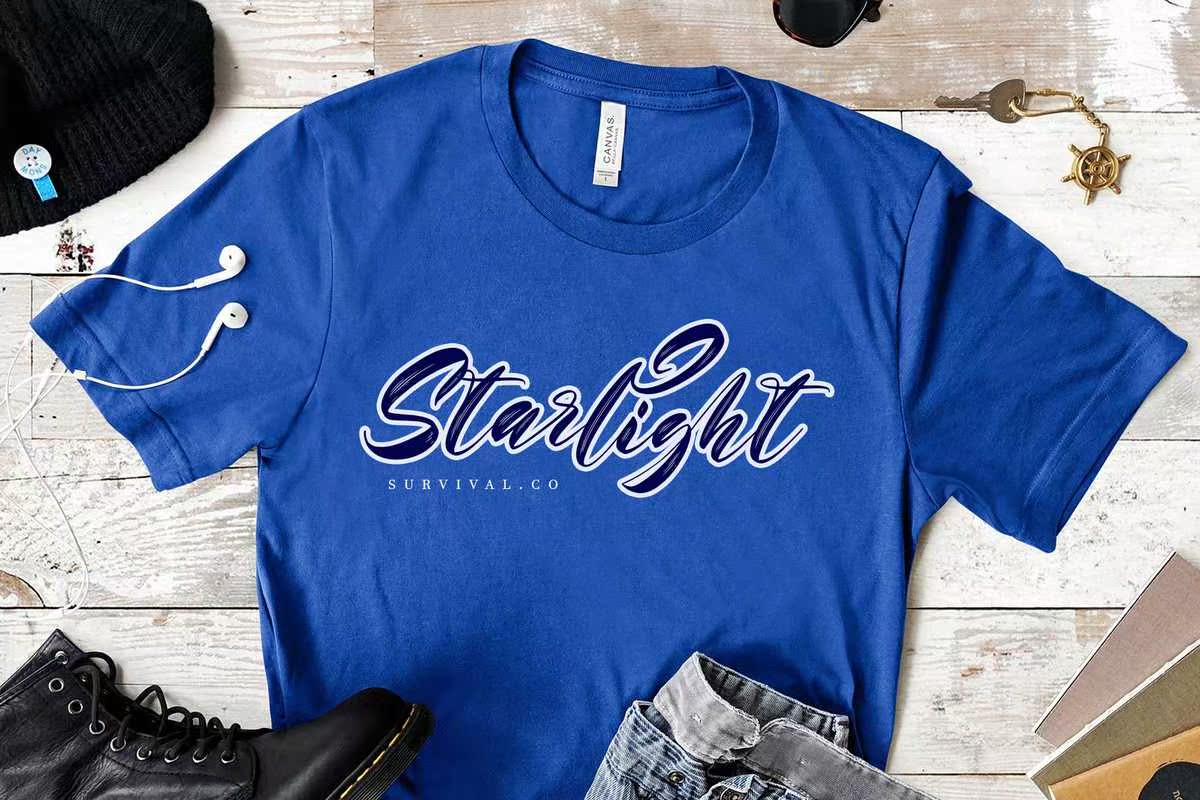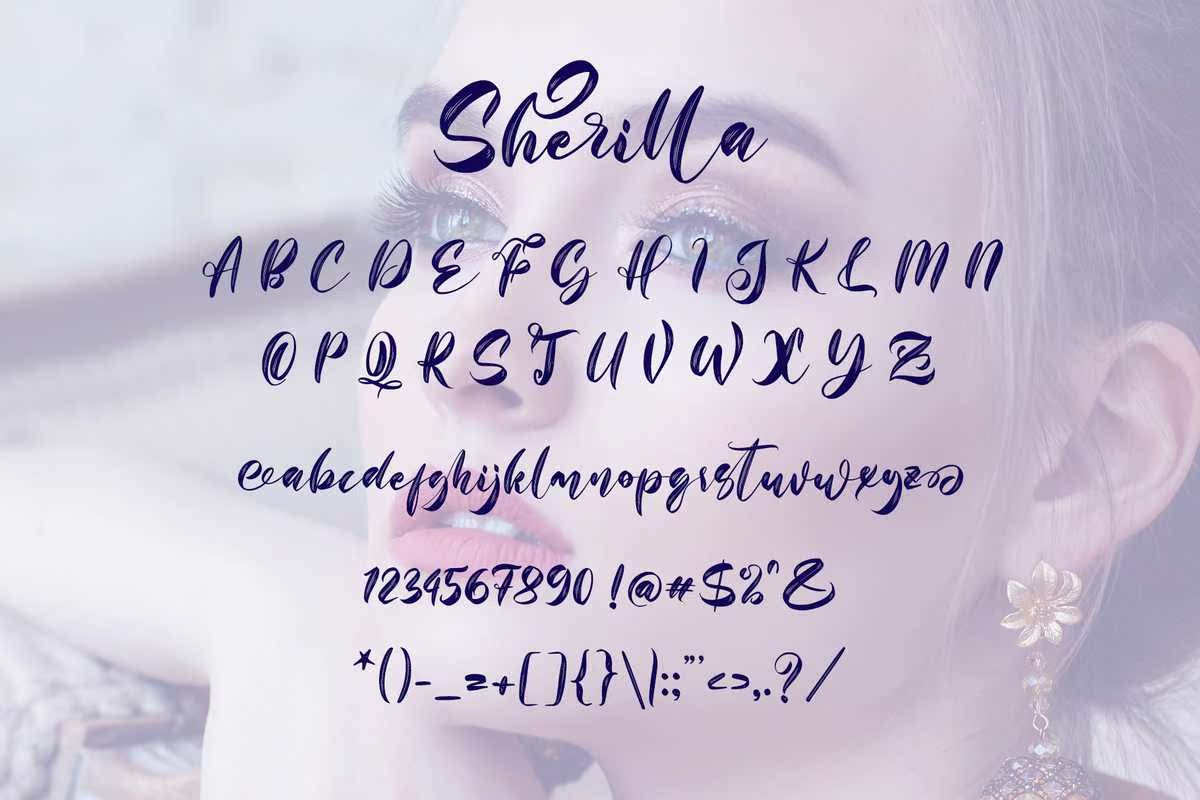
Sheilla是一款精美、精致的系列服装。它是一款优雅、时尚的服装,可用于制作日志、品牌、邀请函、文具、婚礼设计、社交媒体等等!这个字体是经过编码的,意味着你可以访问所有的符号和SWASHEASE!Sheilla是一款精美、精致的系列服装。它是一款优雅、时尚的服装,可用于制作日志、品牌、邀请函、文具、婚礼设计、社交媒体等等!这个字体是经过编码的,意味着你可以访问所有的符号和SWASHEASE!